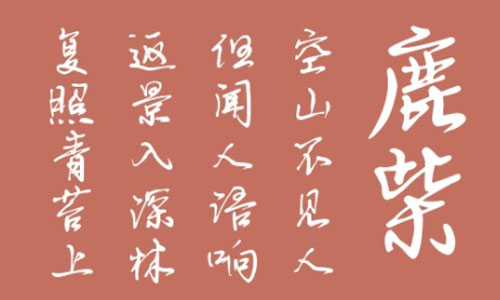
游夢(mèng)手跡字體是一款字跡連貫、頗有草書風(fēng)骨的個(gè)性手寫字體,字體效果極佳,筆走龍蛇、氣質(zhì)磅礴,同樣是鋼筆書法字體,卻有著毛筆字體的大氣飄逸,不適合細(xì)膩文字的閱讀,但在logo設(shè)計(jì)、標(biāo)題創(chuàng)意上有著杰出的視覺呈現(xiàn)。歡迎此字體的朋友前來下載使用。